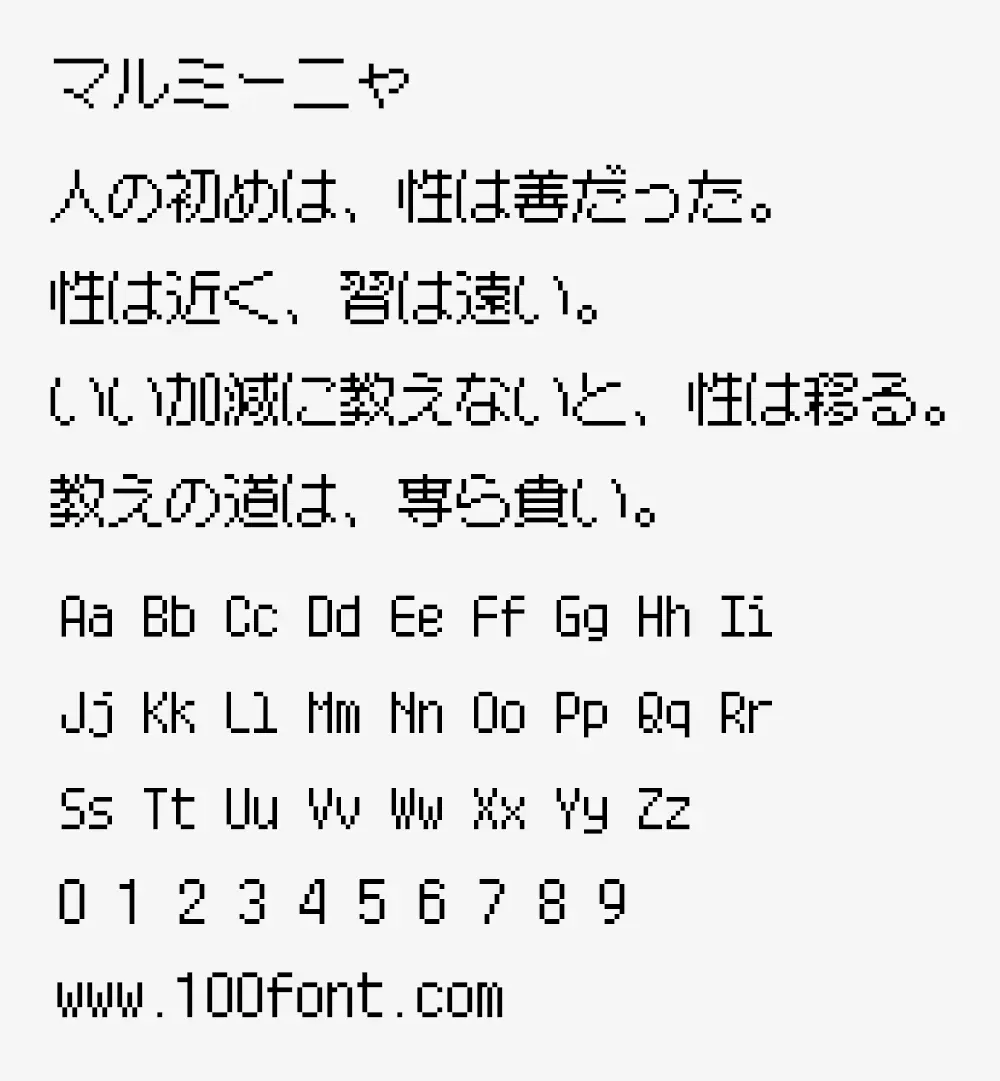
MaruMinya(マルミーニャ)是一個基於12像素大小的圓形哥特體像素字體,具有大字形和廣泛留白的特點,通過整齊排列的像素佈局實現了良好的可讀性。“可愛”中也有“認真”,是可以在廣泛的用途中貼近像素表現的字體。
充實的漢字收錄數,收錄JIS第一水平漢字2965字、第二水平漢字3390字,印刷標準字體也對應,適合包含廣泛的漢字的日語文本。※不支持豎寫。
■ピクセルのかわいさ、詰め込みました。
12ピクセルサイズをベースにした、丸ゴシック體ピクセルフォントです。
大きな字面と広いフトコロを持ち、整理されたピクセルの配置により、十分な可読性を発揮します。
「かわいさ」の中にも「まじめさ」があり、幅広い用途でピクセルの表現に寄り添うことができるフォントです。
■充実の漢字収録數。
JIS第1水準漢字2965字、第2水準漢字3390字を収録。
印刷標準字體にも対応、幅広い漢字を含む日本語テキストに適しています。
※縦書きには非対応となっています。